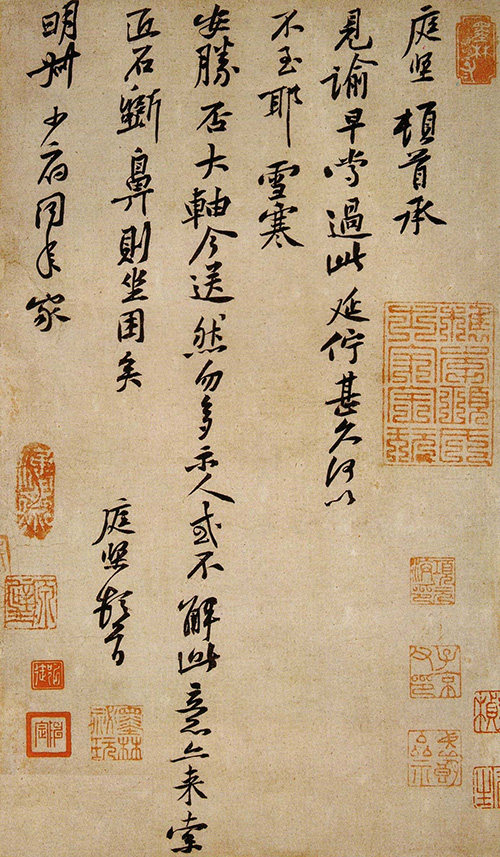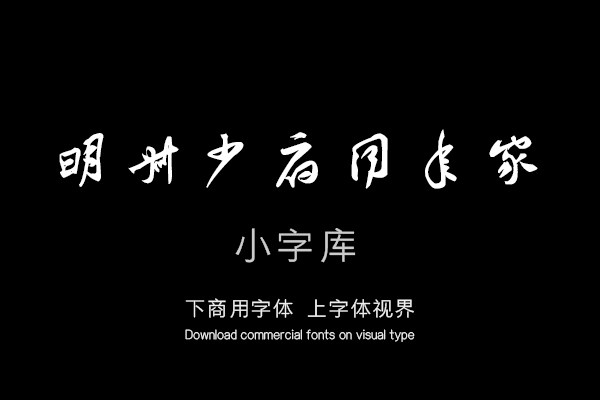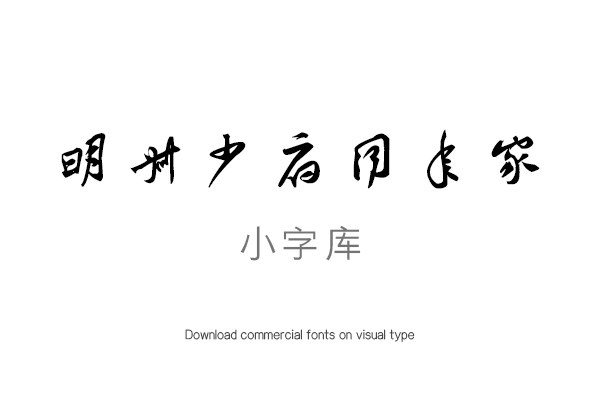
汉标黄庭坚行书雪寒帖
黄庭坚行书尺牍赏析《雪寒帖》亦称《明叔少府》、《致明叔少府尺牍》,纸本28.8 × 17.5cm,凡6行,61字。台北故宫博物院藏。 黄庭坚《雪寒帖》无书写时间......
庭坚顿首,承见谕,早尝过此,延伫甚久,何以不至耶。雪寒,安胜否?大轴今送,然勿多示人,或不解此意亦来索,匠石斫鼻则坐困矣。庭坚顿首。明叔少府同年家。